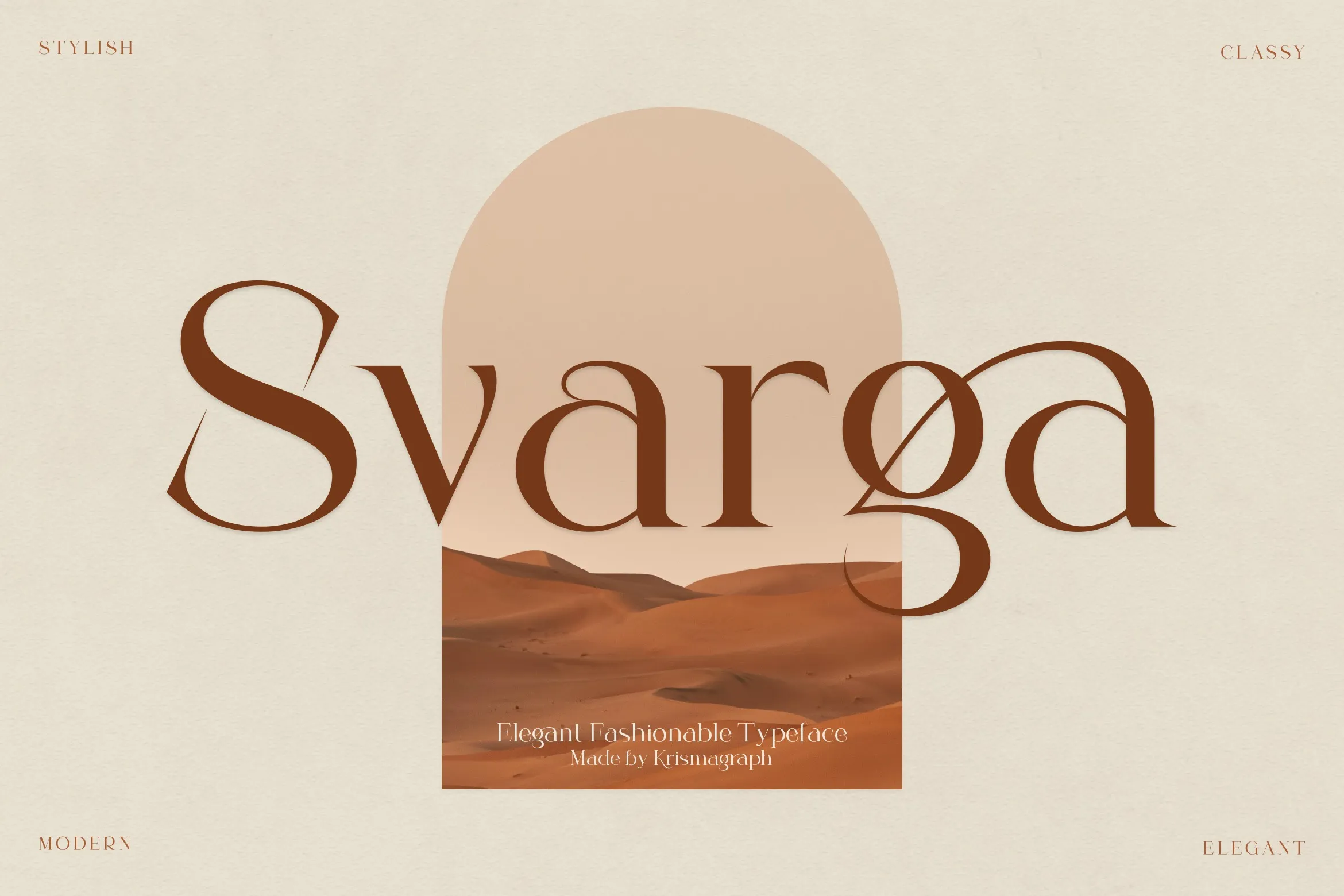
Svarga Font – Download Grátis
A Svarga Font é uma elegante fórmula serif que mantém a simplicidade clássica de suas raízes. Ao modernizá-la com curvas únicas e detalhes bem cortados, ela ganhou um toque nostálgico, tornando-a um dos fonts memoráveis mais desejados no mercado atual. Perfeita tanto para logotipos quanto para revistas e mídias sociais, esta fonte combina modernidade com uma paleta nostálgica que faz dela a escolha ideal para designers procurando por elegância, estilo sofisticado e modernidade. Se você está em busca de um toque refinado para seus projetos gráficos, Svarga é uma ótima opção, pois já vem pronta para ser usada em conjunto com outros elementos de design, garantindo harmonia e consistência visual.